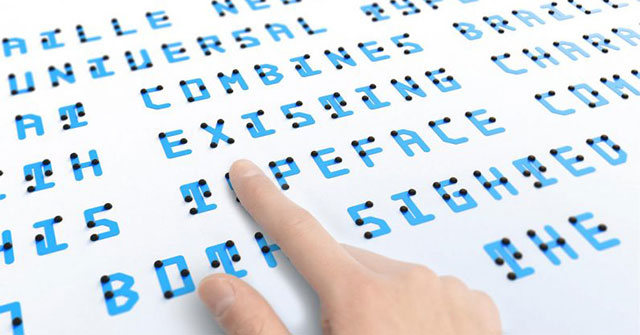
Trong nỗ lực mang đến chữ Braille cho nhiều người gặp vẫn đề về thị giác, giúp họ xem các bảng điện tử hay giấy in, nhà thiết kế đến từ Tokyo Kosuke Takahashi đã đưa ra 1 giải pháp độc đáo, kết hợp các kí tự của chữ nổi với tiếng Anh và Nhật Bản.
Các chữ cái trong kiểu chữ Braille Neue của Takahashi gồm các kí tự, bên trên là những dấu chấm tròn đen (của chữ nổi Braille dành cho người khiếm thị). Cách này sẽ giúp không phải dùng chữ nổi và chữ thường tách rời nhau, giúp dễ dàng đưa chữ nổi vào các văn bản.
Cách kết hợp chữ nổi với kí tự chữ Latin
Takahashi tạo nên kiểu chữ này dựa trên Helvetica Neue, sau đó chỉnh sửa từng chữ cái để đưa thêm các kí tự của chữ nổi. Dự án này sẽ mang đến 2 font chữ chính là Braille Neue, gồm các kí tự Latin và Braille Neue Outline, gồm cả kí tự Latin và Nhật Bản.
Braille Neue cũng có thể hiển thị ở định dạng lớn, phù hợp với các bảng điện tử lớn đặt ở nơi công cộng. Đây không phải là lần đầu tiên có sáng kiến nỗ lực để chữ nổi trở nên phổ biến hơn nhưng là một trong những dự án rất hấp dẫn và thuyết phục. Hy vọng kiểu chữ này sẽ sớm được đi vào sử dụng. Bạn đọc quan tâm có thể theo dõi quá trình phát triển dự án tại đây. https://brailleneue.com/